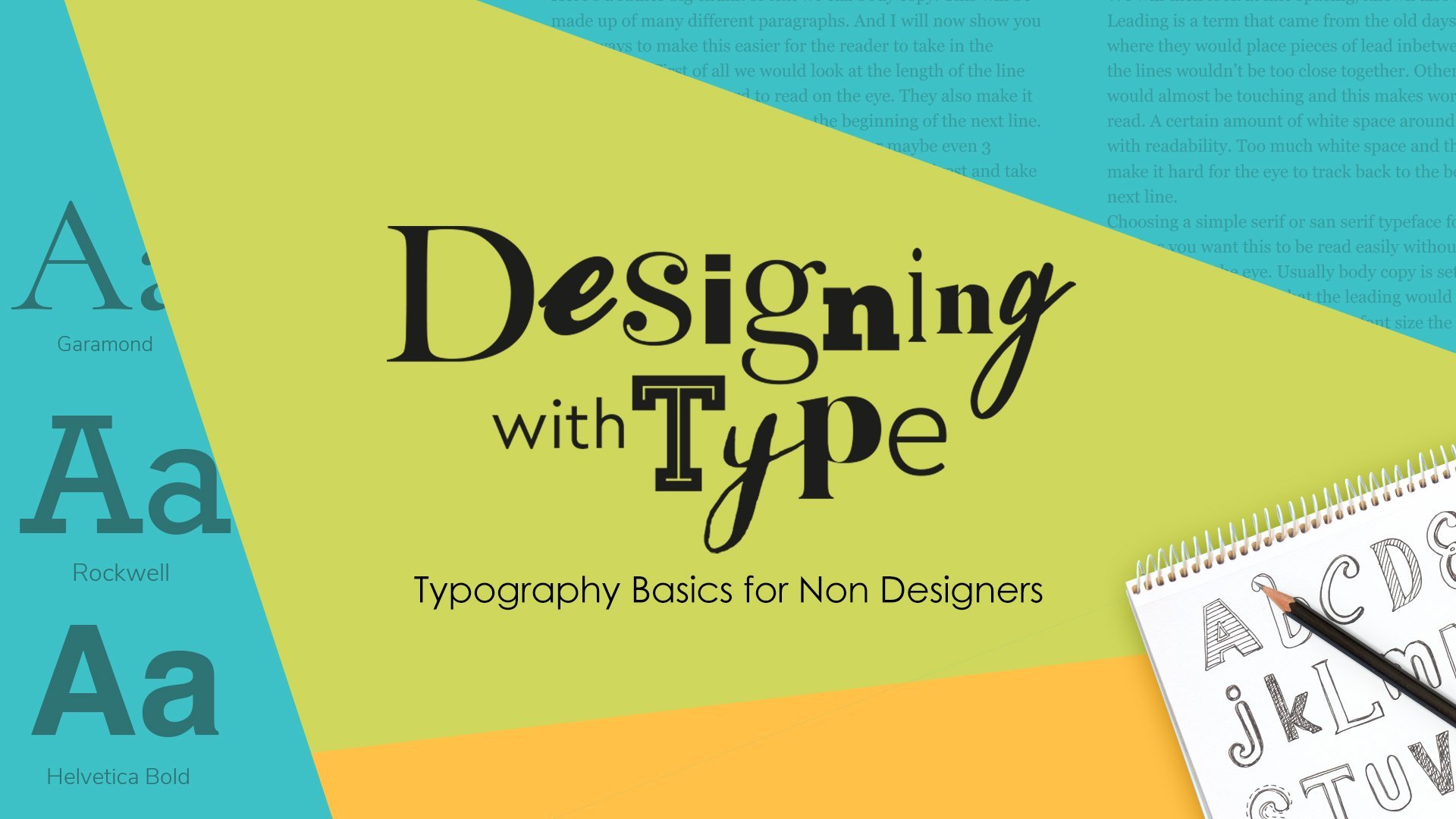
Como projetar com tipo: noções básicas de tipografia para não designers
Sobre este curso
Bem-vindo a este curso de curta duração que introduz não designers na tipografia. Vamos falar sobre como usar o tipo de apresentações e modelos de mídia social com mais eficiência. Vamos explorar o poder por trás de um tipo e como diferentes faces de tipos podem dar diferentes significados. Vamos olhar para o hierachy do tipo, como criar uma cópia do corpo para que seja fácil de ler e falar sobre o kerning.
Este é um curso curto de 20 minutos cheio de informações úteis que lhe dará mais confiança ao trabalhar com o tipo!
1. Apresentação: Bem-vindo a esta aula, Designing with Type, Typography for Non-Designers. Onde mostrarei algumas das minhas dicas e truques sobre como usar fontes e tipos de letra. Falaremos sobre a emoção por trás de um tipo de letra. Como criar um layout de texto. Você pode engajar seu espectador para ler mais e algumas dicas sobre como trabalhar com a cópia corporal, para que as pessoas possam ler e digerir com facilidade. Esta aula é voltada especificamente para não designers. Isso é para pessoas que usam tipos para apresentações ou gráficos de mídia social, mas não tiveram nenhum treinamento em tipografia. Ao final deste breve curso, você se sentirá mais confiante ao usar o tipo e como usá-lo de forma eficaz para comunicar a mensagem certa ao seu público. Olá. Sou Faye Brown e ensino no Skillshare desde 2012. Sou especialista em design gráfico e branding com sede no Reino Unido. Eu sou um grande nerd de tipografia que poderia falar sobre tipos de letra o dia todo. No entanto, nesta aula, vou condensar isso em uma aula curta e rápida de 20 minutos que lhe dará o conhecimento para usar a tipografia forma mais eficaz, então vamos nos aprofundar. 2. O que é tipografia?: O que é tipografia? Simplificando, a tipografia é a arte de organizar ou criar formas de letras. Gosto de descrever a tipografia como sua voz visual, embora na verdade não seja isso que é muito design gráfico. É comunicar uma mensagem sem precisar falar. Nós analisamos tudo visualmente. Ter conhecimento de algumas dicas e truques de tipografia é uma ferramenta muito útil. Eu realmente fiquei fascinado pela tipografia quando fiz meu curso de design gráfico. É uma área muito grande para cobrir. Hoje vamos nos concentrar principalmente nos tipos de letra e em como cada um pode ter sua própria personalidade. À medida que avançamos, apresentarei alguns termos tipográficos e algumas dicas sobre como criar o layout de blocos de texto que sejam interessantes para o leitor seguir. Existem vários projetos que você pode escolher para esta aula. Você pode escolher um ou todos eles, se quiser. O primeiro será caçar o alfabeto. Você pode tirar uma câmera de um lado para outro e pesquisar cada letra do alfabeto, idealmente todos os estilos diferentes. Aqui está um que eu fiz em uma recente pausa em Londres. Este projeto realmente ajuda você a perceber todos os diferentes estilos de fontes. À medida que avança, pense em quais estilos estão sendo usados para o que e como esses tipos de rostos fazem você se sentir? Talvez seja uma loja. O tipo de letra faz com que pareça caro ou mais econômico? Isso faz com que pareça sério ou divertido? O tipo de letra parece acessível ou talvez um pouco assustador? O tipo de letra é fácil de ler? Como alternativa, talvez você queira fazer este projeto em um dia chuvoso, então você pode usar revistas para encontrar todas as letras do alfabeto. Tente usar revistas diferentes e veja como elas estão usando tipos de letra de maneiras diferentes dependendo do assunto. revista Minecraft do meu filho usa fontes muito diferentes Home Magazine ideal, por exemplo. Pense em tudo isso ao coletar suas cartas. Uma alternativa para isso é escolher uma letra, talvez seja a primeira letra do seu nome e tentar encontrar o maior número possível de exemplos diferentes dessa letra. Isso pode ser mais difícil dependendo do seu nome. Aqui está um exemplo de alguns F's que encontrei no pinterest.com. Mas é mais divertido se você puder sair e dar uma olhada em revistas. Se você pudesse encontrar uma mistura de letras maiúsculas e minúsculas, isso seria bom. Letras maiúsculas são maiúsculas. Eles são chamados de maiúsculas, pois nos dias de uso do tipo metal, as letras maiúsculas eram mantidas na gaveta superior. Caso você já tenha se perguntado por que eles eram chamados de maiúsculas. Ao escolher uma letra, ele ajuda você a ver todas as diferentes maneiras pelas quais essas letras podem ser desenhadas, mesmo que as formas básicas sejam as mesmas. Também está incluído nos recursos da aula um PDF com alfabetos e números de todos os estilos diferentes. Você encontrará isso na guia de recursos. Se você tiver papel vegetal ou um pedaço fino de papel branco, experimente desenhar sobre essas letras. É uma maneira muito boa de entender formas de letras e diferentes estilos de fontes. Além disso, aqueles um pouco mais confiantes em desenhar, tente redesenhá-los sem traçar. Esses são seus projetos. Vou continuar voltando a eles, mas agora vamos falar mais detalhadamente sobre como os tipos de letra podem ter sua própria personalidade e como o tipo de letra que você escolher pode mudar a maneira como você lê uma palavra. 3. Como escolher tipos de faces: Escolhendo o tipo de letra certo. Um tipo de letra pode realmente evocar uma emoção? Vamos dar uma olhada. Gosto de usar a palavra amor e escola para este exercício. Vamos começar com amor. Aqui estão quatro tipos de letra diferentes ilustram exatamente a mesma palavra. Como cada um faz você se sentir? A cor também pode desempenhar um papel importante no design visual, mas eu propositalmente não estou incluindo a cor nessas opções, ela é puramente baseada no tipo de letra. Se quiser, pause o vídeo e faça algumas anotações mentais sobre como esses tipos de letra podem ajudar a ilustrar diferentes formas de amor. Acho que o canto superior esquerdo é um amor muito amigável. É bem clássico. É um pouco caseiro, se é uma palavra. É um amor fácil de fluir. O canto superior direito é um pouco diferente. Parece um amor meio assustador e duro. Eu posso imaginar isso na capa de um álbum de uma banda de rock,. O amor do canto inferior esquerdo é bastante moderno, é muito confiante e ousado. Em seguida, uma forma suave com as bordas curvas e a redondeza de algumas das formas e formas. O amor no canto inferior direito parece muito inocente e infantil. É o amor que uma criança pode ter por seu ursinho de pelúcia favorito. Agora, se você viu ou não essas palavras exatamente da mesma forma que eu ou não, não importa, mas espero que haja semelhanças entre nosso pensamento. Você provavelmente não veria o canto superior direito em muitos convites de casamento. Apenas escolhendo diferentes tipos de letra, podemos definir como o leitor pode se relacionar com a palavra. Vejamos a palavra escola, que não é uma palavra tão emocional. Novamente, pause o vídeo e pense como você se relaciona com essas opções. Como você acha que cada escola poderia ser? O canto superior esquerdo para mim, parece muito tradicional e adequado. Eu esperaria que a escola estivesse bem estabelecida e séria em sua abordagem à educação. O canto superior direito parece mais divertido. Talvez isso seja bom para a escola de dança. O canto inferior esquerdo, este me lembra de uma faculdade esportiva americana, estou sentindo a impressão de ser uma escola muito esportiva. O canto inferior direito parece talvez uma escola de palco, algo bem barulhento e sem graça. Você também pode fazer esse exercício com seu nome. Digamos que eu estivesse criando um logotipo para alguém chamado Charlie Hooper. Não sabemos qual é o gênero de Charlie, não sabemos o que Charlie faz, mas só de olhar para esses tipos de letra, podemos começar a formar ideias em nossa cabeça sobre o que Charlie faz. Você pode tentar encontrar um tipo de letra para si mesmo. Há um ótimo site chamado Font Squirrel, que está cheio de fontes gratuitas. Você pode clicar em alguns dos termos aqui como ponto de partida e clicar em Test Drive, onde você pode digitar seu nome e ver sua aparência. Pense na sua personalidade. Parece certo para você? Este provavelmente é um pouco chique demais para mim, por exemplo. Gostei do fato de ser muito amigável e ousado, mas tem um pouco de sucesso e talvez um pouco demais e, na verdade, é muito difícil de ler. Outro ótimo site para procurar tipos de letra é o creativemarket.com. Você pode pesquisar fontes e, se clicar em um pacote, poderá testá-las novamente de uma só vez. Esses custam dinheiro, mas ainda é um exercício muito divertido de fazer. Isso me ajuda a compará-los facilmente e ver o que pode ser melhor para mim. Era de um pacote moderno, mas talvez você queira escolher algo muito mais decorativo e descolado como este. Pense na sua personalidade e no estilo que combina com você. Esse é basicamente o processo pelo qual eu passo quando crio logotipos. Pensando na personalidade das cartas e em como elas refletem a empresa ou pessoa para a qual estou projetando. Experimente você mesmo. O que o ajudará a começar com isso é conhecer um pouco sobre classificações de tipos, do serviço ao autoatendimento, passando por fontes de script e escrita à mão. Agora, daremos uma olhada em alguns deles para ajudá-lo em suas pesquisas. 4. Digite classificações: Serifa. Uma fonte Serif tem pequenos traços no final dos caracteres. serifas são geralmente associadas a fontes mais tradicionais, como Times e Garamond, mas muitas das fontes mais modernas usam serifas, seja entre colchetes, como Garamond aqui, ou laje Serif como Rockwell ou uma cunha Serif como Birch. Muitos livros são escritos usando fontes Serif tradicionais, como Garamond. A ajuda serosa forma uma ligação entre cada uma das letras, o que, por sua vez, ajuda o olhar do leitor a fluir através de uma linha ou parágrafo do tipo. Os tipos de letra Serif mais tradicionais podem ajudar algo a parecer bastante profissional, confiável e estabelecido, mas também podem transmitir a sensação de ser um pouco chato. Sem serifa. Sans Serif é simplesmente um tipo de letra sem Serifs, sans, ou seja, sem. O tipo de letra Sans Serif mais famoso talvez seja Helvetica, como visto aqui no metrô de Nova York. Uma família tipográfica simples, como esta cópia do corpo, que está em Montserrat, é fácil de ler e facilita a leitura para o leitor. Muitas vezes vemos os tipos de letra Sans Serif usados em sites, embora os Serifs estejam voltando um pouco. letra Sans Serif em geral comunicarão um pouco mais de uma abordagem moderna aos negócios, amigável e acessível. Se você está buscando um mercado mais jovem, pode optar por um estilo Sans Serif. Todos os tipos de letra geralmente se encaixam em Serif ou Sans Serif, mas há outros estilos em termos a serem considerados. de letra em estilo de script foram desenvolvidos no século 17 com base em técnicas de escrita usando caneta e tinta. Desde então, outros estilos de roteiro desenvolveram e se tornaram muito populares. Os estilos de roteiro podem realmente variar em suas mensagens, de formais e elegantes a letras pretas pesadas, ousadas e barulhentas. estilos de quadrinhos podem ser divertidos, dependendo do uso. Tente evitar Comic Sans. Comic Sans tem sido usado, usado em demasia e também usado para coisas inapropriadas, como sinais de alerta. Há um sinal de alerta em nossa cidade sobre ser eletrocutado e está na Comic Sans. Tem uma reputação um pouco ruim entre os designers. Embora, aparentemente, seja um dos tipos de letra mais fáceis para as crianças lerem. de letra decorativos adotam muitos estilos, como Budmo Jiggler e Rosewood, eles só seriam usados para realmente chamar a atenção, então títulos, pôsteres e possivelmente logotipos da maneira certa. decorativo também pode incluir estilos de roteiros. Estilos de máquina de escrever como este são bastante autoexplicativos. Esse estilo pode funcionar muito bem para designs de estilo de definição de dicionário. Os estilos de estêncil geralmente são letra que têm quebras nas formas de letras. Eles são frequentemente usados para referências ao estilo do exército e também para documentos ultrassecretos. exibição de muitos estilos anteriores sobre os quais falamos estaria nessa categoria mas ao fazer pesquisas de fontes, essa categoria mostraria opções que são ótimas para textos maiores, portanto, cabeçalhos e pôsteres, em algum lugar também funcionam para logotipos. Escrito à mão. Eles também podem se encaixar no script por causa do estilo, mas os tipos de letra manuscritos são muito populares e podem adicionar uma sensação amigável e pessoal ao texto. Não é só o tipo de letra que pode ajudar na comunicação de uma mensagem. Usar tamanho e peso também pode ser usado de forma muito eficaz. Vamos dar uma olhada no próximo vídeo. 5. Tamanho e peso: Tamanho e peso. Os próximos slides que você verá geralmente são da mesma família sem serifa chamada Gotham. Dentro dessa família, temos um peso fino até o ultra. As formas das letras são baseadas nas mesmas formas, mas o peso faz com que pareçam muito diferentes. Se quisermos criar uma sensação de calma e sossego, um peso mais magro pode funcionar melhor, mas se quisermos gritar sobre algo ou alertar as pessoas sobre possíveis perigos, um peso pesado e ousado conquistará as pessoas atenção mais rápida. Também podemos usar o tamanho para nos ajudar com nossas mensagens aqui. Podemos sussurrar ou gritar. Vamos ver como isso pode ser usado em algo chamado hierarquia tipográfica. É quando queremos convidar o leitor a entrar e deixar que eu siga as informações para eventualmente ler, talvez como um artigo completo. Vamos tomar isso como um breve exemplo. Digamos que você tenha visto esses dois quadrados aparecerem nas redes sociais ou em um site, qual deles você provavelmente lerá? O da direita convida você a entrar. Ele dá uma ideia do que o resto do parágrafo pode falar em partes digeríveis de informações. Vamos ver como os designers de revistas fazem isso no design do layout. Nós vemos a manchete. É o maior texto da página. Vemos o subtítulo, que é provavelmente o segundo maior texto da página. Também temos um fato adicional que você provavelmente lerá após o subtítulo. Nesse ponto, você provavelmente sabe que se quiser ler o artigo inteiro, o restante do texto é chamado de cópia do corpo. Nossa visão contornou as principais informações muito rapidamente, graças à forma como o texto foi apresentado. Quando se trata de layouts como esse, queríamos garantir que o texto fosse fácil de ler. Alguns tipos de rosto são, na verdade, muito difíceis de ler, embora você possa usá-los em tamanhos maiores. Essa amizade tipográfica é muito divertida. Como fonte de cabeçalho, funcionaria bem em um pôster. Parece amigável e peculiar. Também é ousado e fácil de ler. No entanto, se usarmos o mesmo tipo de letra para um bloco de cópia do corpo, repente se torna muito mais difícil de digerir. Provavelmente me daria dor de cabeça se eu lesse um parágrafo inteiro escrito com esse tipo de letra. Por que isso? Vamos dar uma olhada no corpo do texto e em algumas dicas para facilitar a leitura de muitos textos. Primeiro, podemos escolher uma fonte com serifa ou sem serifa bastante simples, nada com muito caractere pois isso dificultará a leitura. Salve esses tipos de letra para cabeçalhos. Vamos escolher a Geórgia. Eu configurei isso em 9 pontos, o que geralmente é um bom tamanho para a cópia do corpo. Há algumas coisas que podemos fazer agora para tornar isso mais fácil para o leitor. Primeiro passo, este é um grande bloco de texto com linhas muito longas. Na verdade, é muito difícil para os olhos lerem uma linha de texto tão longa. Vamos dividir isso em duas colunas. Você verá muito isso em revistas. Muito raramente haverá longas linhas de texto. Entre 10 a 15 palavras em uma linha geralmente há uma boa quantidade, ou 60 a 70 caracteres. Por caracteres, quero dizer as letras, a pontuação, os números, etc. A outra coisa que podemos observar é o espaço entre cada uma das linhas. Isso é chamado de liderança. Essas linhas estão bem próximas e fazem com que o texto pareça bastante confuso. Não há muito espaço em branco ao redor das linhas para descansar os olhos. Veja o que acontece quando eu altero o espaçamento entre as linhas da segunda coluna, repente parece um pouco mais fácil de ler. Embora, se formos longe demais, isso possa significar que acho difícil encontrar reforços no início da próxima linha. É conseguir esse equilíbrio feliz. Sempre me disseram que se você tivesse um ponto de tamanho de tipo em torno de nove pontos, geralmente, um bom espaçamento entre linhas seria 4 pontos acima disso, então 12 a 13 pontos. Isso dependerá do programa que você está usando para ver esses valores com facilidade. Eu uso muito o Adobe Illustrator, mas esse é um programa caro. No Canva, você não tem tanto controle sobre o espaçamento entre linhas, então você está confiando em seus olhos. Espero que essas pequenas dicas tenham ajudado no que procurar. 6. Kerning: Há muitos termos tipográficos sobre os quais eu poderia falar, mas é muito para entender e, na verdade, é algo para explorar mais se você entrar no design gráfico com mais profundidade. Mas mais um termo que eu gostaria de apresentar a vocês é kerning. Kerning é o espaço entre as letras. Depois de conhecer o kerning, você começará a detectar o kerning ruim em todos os lugares. Vamos começar com a palavra. Geralmente, a maioria dos tipos de letra tem um kerning predefinido quando você os usa em um computador. Mas às vezes os gratuitos podem não ser bons e você mesmo precisa ajustar o kerning. Talvez eu queira aproximar esse A do T, pois há uma pequena lacuna. Estou preocupado que, se essa fosse uma palavra importante em um pôster, essa lacuna possa dificultar a legibilidade. Talvez pareça arte em vez de começar. Você pode usar o espaçamento entre letras a nosso favor se quisermos adicionar mensagens a uma palavra. Rapidamente, eu poderia fechar o espaçamento entre letras. Além disso, eu poderia colocá-lo em itálico para que pareça que está indo para frente. Para devagar, eu poderia ampliar esse espaço para que a palavra seja lida mais devagar. Se você estiver criando um pôster, eu não sugiro que você comece a mexer no espaçamento entre letras de cada palavra, pois ela começará a parecer confusa e inconsistente. Mas kerning é um bom termo a ser conhecido quando se trata de tipografia. 7. Os seus projetos: Então, vamos relembrar esses projetos. Agora você sabe muito mais sobre tipos de letra, a emoção que um tipo de letra pode transmitir e as diferentes classificações de fontes. Saia e explore e veja quantas você consegue encontrar. Faça uma anotação mental de quais tipos de letra foram usados para quê? Eles ajudam a transmitir a mensagem? Ou uma fonte de estilo melhor funcionaria melhor? Crie seus alfabetos a partir de fotos ou recorte de revistas e divirta-se realmente conhecendo melhor as formas de letras. Então, por que não tentar criar seu próprio tipo de letra? Você pode usar um site como o calligraphr.com que tem uma inscrição, embora você possa começar gratuitamente. Depois, você pode imprimir o formulário e preenchê-lo com suas próprias cartas. Você pode simplesmente desenhar suas próprias letras à mão. Pense nas formas das letras: ao fazer isso, algumas letras podem demorar algumas vezes para serem perfeitas. Você pode usar Lego, recortes de papel, blocos de massa, selos estampados de batata, pedras, fitas, moedas. Talvez use suas iniciais para criar formas criativas de criar cartas. Mas, principalmente, divirta-se um pouco. 8. Conclusão: Essa é a sua introdução à tipografia. Tenho duas outras aulas sobre esse assunto, A Arte da Topografia. Foi minha primeira aula de Skillshare que abordou essa área com muito mais profundidade. Escolher os tipos de letra certos explora essa área um pouco mais. Mal posso esperar para ver seus projetos, pois adoro tipografia e adoraria ver seus alfabetos de todo o mundo. Se você quiser se juntar ao meu grupo dedicado no Facebook e aos meus alunos do Skillshare, faça isso. Vou colocar um link nas notas abaixo neste vídeo. Espero que você tenha gostado dessa aula. Por favor, deixe-me alguns comentários se você fez isso, e sobre quais outros assuntos você também gostaria de uma aula curta.